Más de 35 de las mejores fuentes en Canva: la lista definitiva de fuentes de Canva para creativos
Publicado: 2023-01-06Si está buscando las mejores fuentes en Canva probando todo usted mismo, es posible que esté allí por un tiempo. La herramienta tiene innumerables fuentes que puede usar en su diseño, y tratar de encontrar la mejor es un poco abrumador. Además, es posible que termine pasando más tiempo del que le gustaría hacerlo.
Afortunadamente, no es necesario que hagas eso.
Si quieres saber qué fuentes en Canva deberías considerar usar, estás en el lugar correcto. Este artículo cubre más de 35 de las mejores opciones, lo que facilita la elección de la que crea que funcionará mejor para usted.
¿Te suena interesante? Fantástico. En ese caso, comencemos.
Comprender las fuentes de Canva más populares
Antes de sumergirnos en la lista de fuentes de Canva, cubramos un par de conceptos básicos. La mejor manera de usar estas fuentes de Canva es creando una cuenta y usando el servicio. Si bien Canva Pro tiene varios beneficios, también puede encontrar una amplia gama de fuentes cuando usa la versión gratuita.
Puede utilizar estas fuentes en numerosos diseños. Funcionan bien en los banners de los canales de YouTube y en las imágenes de portada de los blogs, pero esas no son sus únicas opciones. También puede agregar estas fuentes para infografías, presentaciones, anuncios y más.
Algunos sitios web también te permitirán descargar fuentes para Canva, dándote más opciones si quieres probar otras cosas.
Cuando utilice una fuente en Canva, vaya a la opción Texto en la barra de herramientas de la izquierda. En el banner de búsqueda de texto en la parte superior, puede buscar la fuente que desea usar.
Con todo eso fuera del camino, veamos las mejores fuentes en Canva.
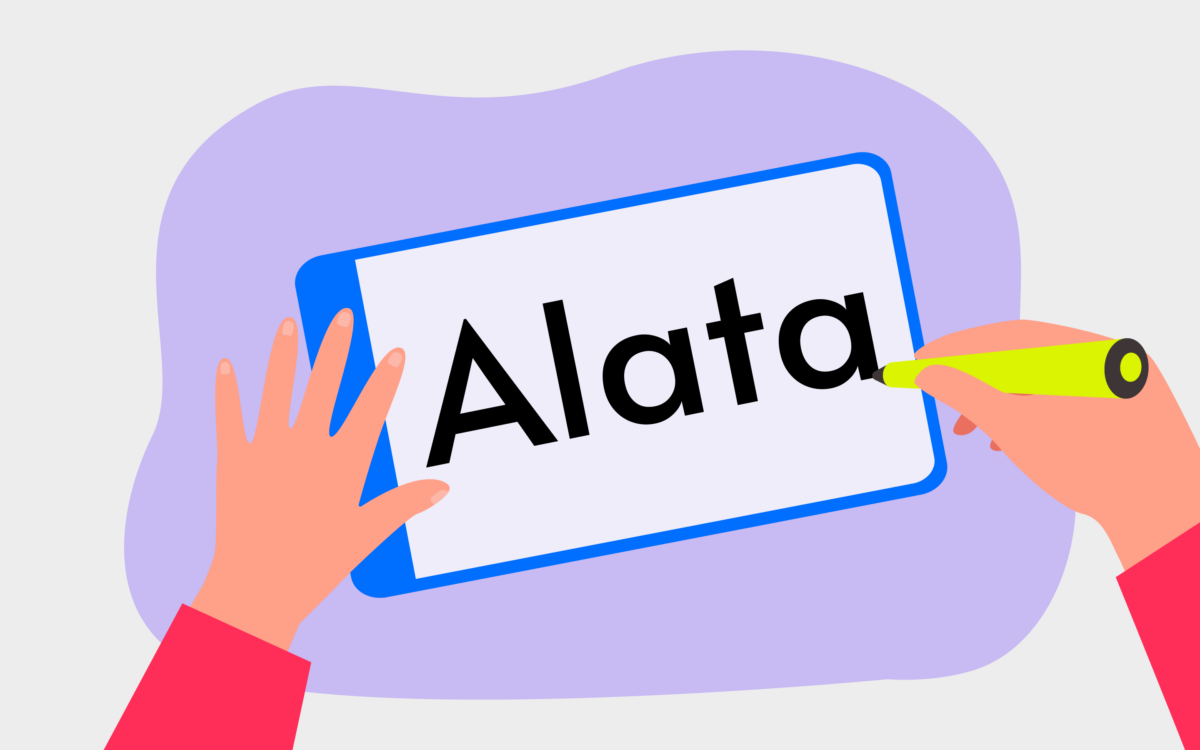
1. Alata
Alata es el primer lugar en el que comenzaremos en esta lista de las mejores fuentes en Canva. La fuente es bastante estándar y presenta un diseño elegante. Este es un excelente punto de partida si está buscando algo que no sea quisquilloso.
Si elige Alata, creemos que funcionaría mejor en la copia de la página de destino y para una infografía. La razón principal de esto es que es fácil de leer y se destaca desde lejos. También puede pensar en usarlo en anuncios.
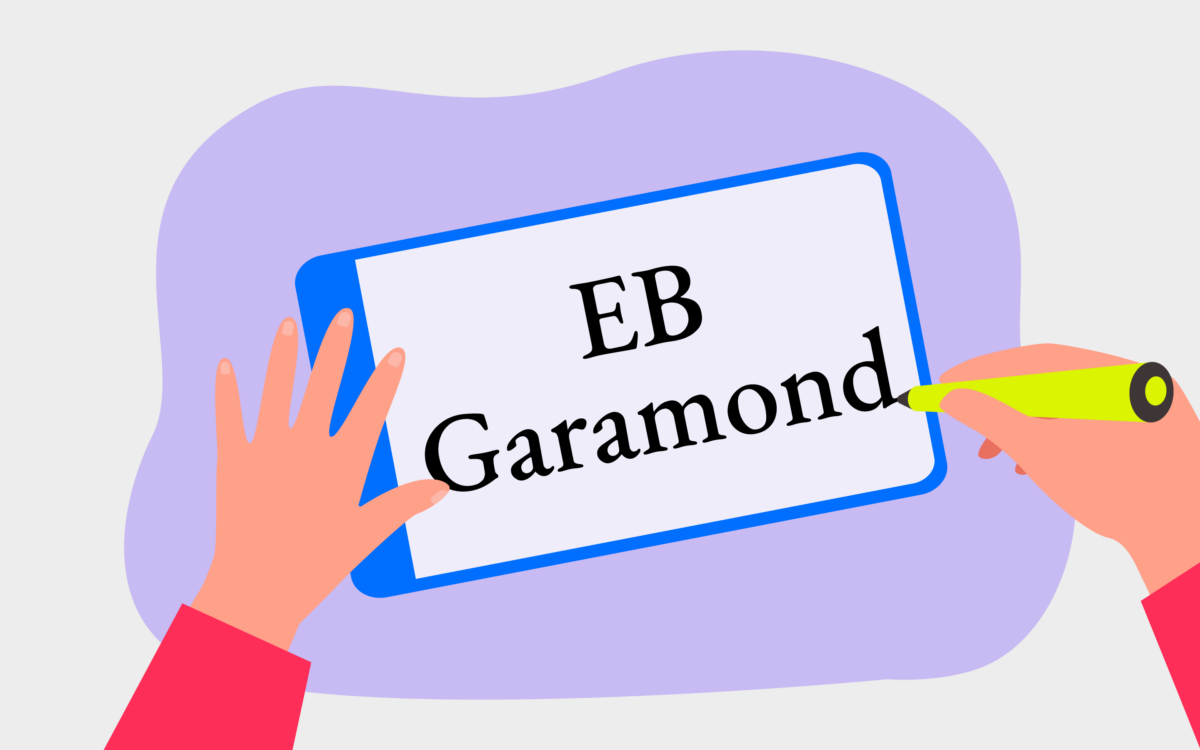
2. EB Garamond
Si ha usado Microsoft Word en el pasado, seguramente habrá oído hablar de Times New Roman. También estará bastante familiarizado con su apariencia. EB Garamond es una versión bastante similar y es una de las mejores fuentes de Canva para principiantes.
EB Garamond trabajará con marcas que busquen una apariencia más antigua. También puede usarlo en la copia de su página de destino y en cualquier currículum que diseñe dentro de Canva.
3. Serif PT
Si EB Garamond es demasiado anticuado para usted, considere usar PT Serif en su lugar. Este diseño es un poco más elegante y delgado que la fuente Canva mencionada anteriormente, lo que significa que es una mejor opción si su marca es más moderna.
PT Serif puede funcionar con encabezados de LinkedIn si es más una empresa de estilo corporativo. También puede usar esta herramienta con equipos relacionados con la escritura, como soluciones de edición. Y si es un escritor o editor independiente, es posible que desee usarlo de manera similar, principalmente si trabaja en libros.
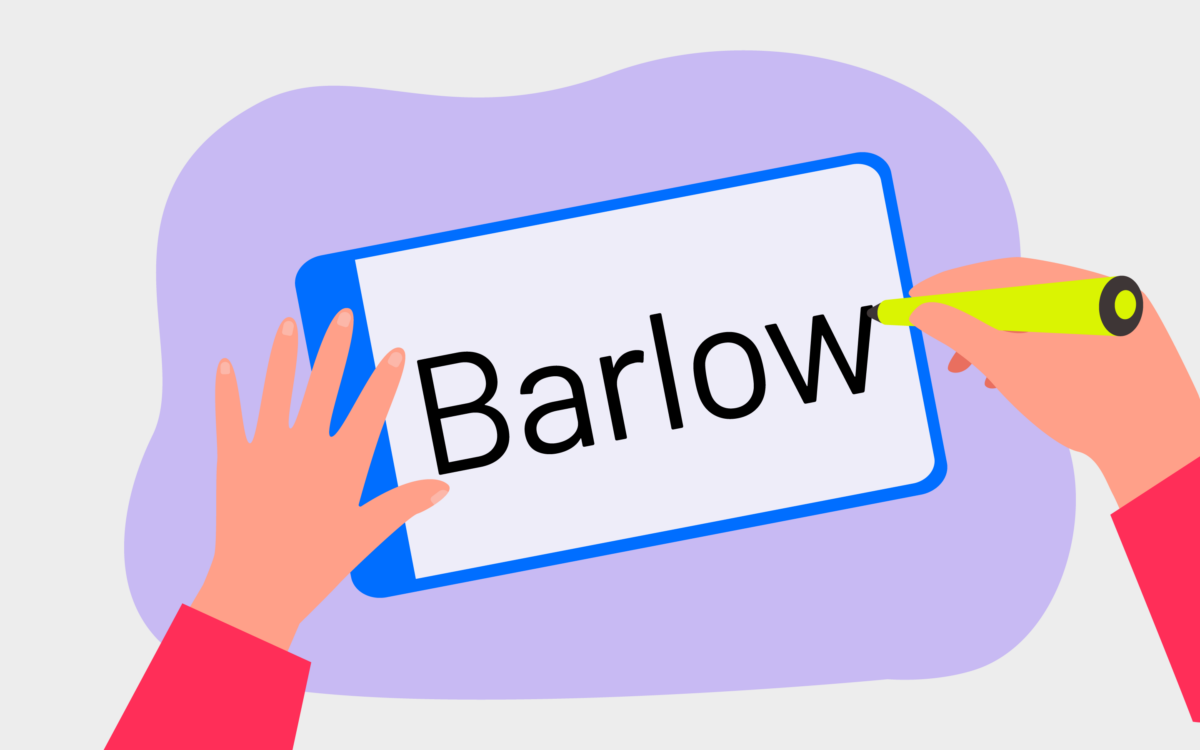
4. Negrita Barlow
Todavía no hemos cubierto ninguna fuente en negrita en nuestra lista de las mejores fuentes de Canva, por lo que pensamos que ahora sería un buen momento para cambiar eso. Barlow Bold es una de las fuentes en negrita más limpias de la aplicación y puede usarla para que su diseño se destaque como creativo.
Barlow Bold funciona con carteles y también es útil para títulos infográficos. También puede usarlo en los encabezados de los currículums. Además de eso, funciona con presentaciones. Es mejor usar esta fuente con moderación si es para el texto principal, ya que al lector le puede resultar complicado seguirla.
5. Arvo
Arvo es más aerodinámico que EB Garamond y PT Serif, pero no es muy diferente. Funciona mejor como parte del cuerpo principal del texto en lugar de usarlo en los encabezados.
La fuente es una excelente opción para campañas de infografía, y puede resultarle útil para usar en cualquier encabezado de redes sociales que pueda tener. También puede usar esta fuente si ejecuta un sitio web centrado en la tecnología.
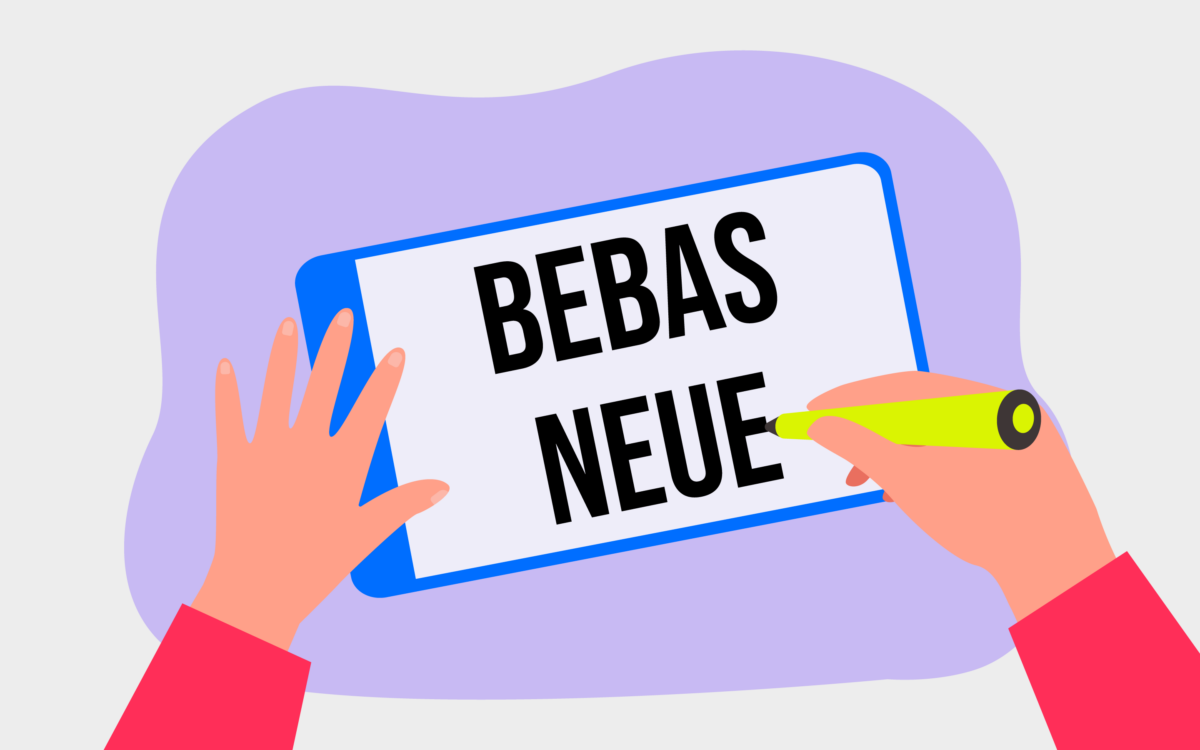
6. Bebas Neue
Otra fuente moderna en la que vale la pena pensar es Bebas Neue, y esta es bastante versátil. Funciona bien como encabezado o título, y puede resultarle especialmente útil si desea crear banners para sus canales de redes sociales, como YouTube.
También vale la pena usar Bebas Neue con cualquier infografía que quieras crear. Además de eso, puede usar la fuente con logotipos que desee diseñar, junto con muchos otros escenarios.
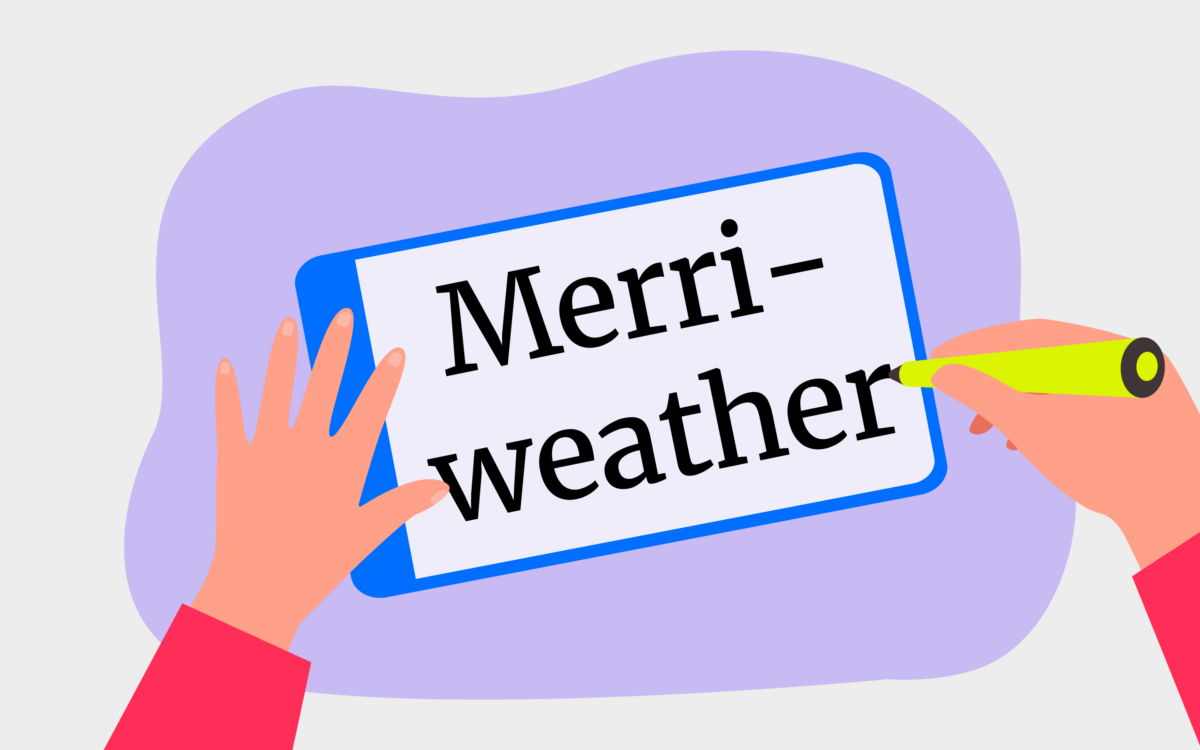
7. Buen tiempo
Merriweather es una fuente similar a algunas marcas de ropa para exteriores. Se destaca sin demasiados problemas, y la fuente también es una excelente opción si desea adoptar un enfoque práctico para sus proyectos de diseño.
Cuando use esta fuente, piense en usarla en campañas de marca y para sus logotipos. También puede funcionar al crear páginas para su sitio web y solicitar a los usuarios que realicen una llamada a la acción, como suscribirse a un boletín informativo.
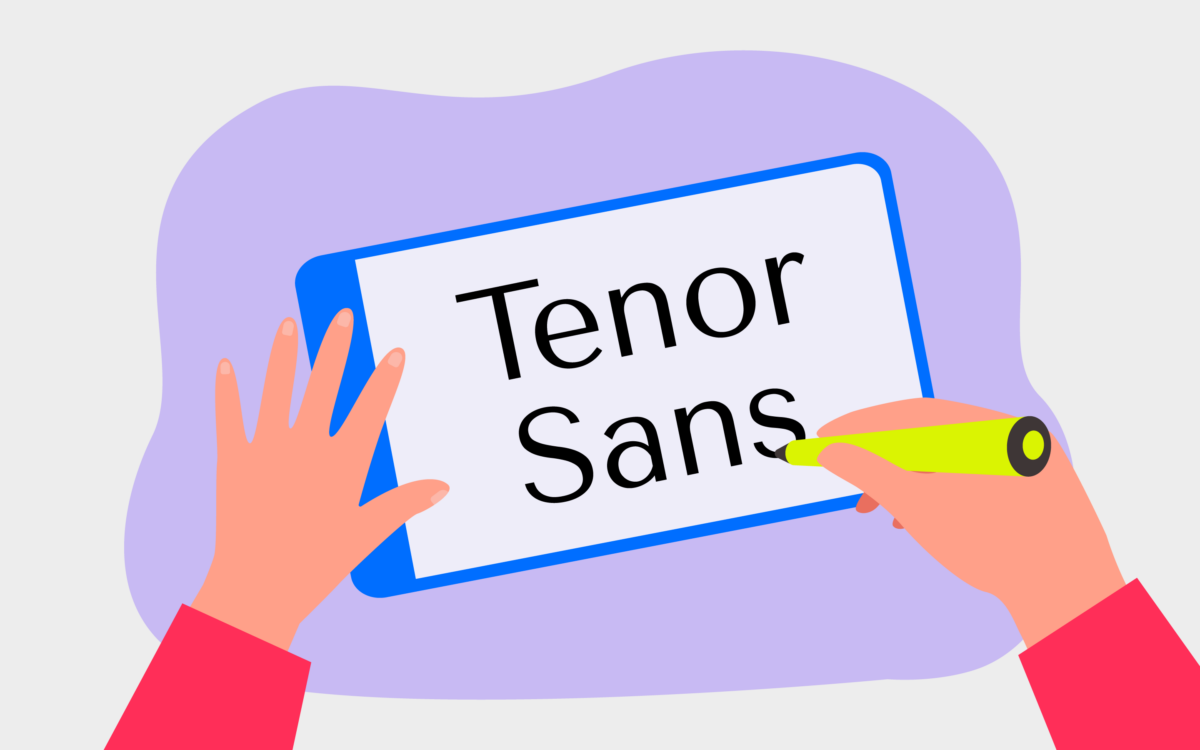
8. Tenor Sans
Tenor Sans es un excelente punto de partida potencial si desea algo que fluya un poco más libremente que Merriweather. La fuente es perfecta como título principal o como algo que usaría en su texto. Es algo moderno pero quizás un poco menos que otros en nuestra lista.
Puede usar Tenor Sans en los encabezados de las redes sociales, que también funciona bien con infografías. Más allá de esas posibilidades, también podría considerar agregar Tenor Sans a las publicaciones de las redes sociales y videos de formato corto, como Instagram Reels.
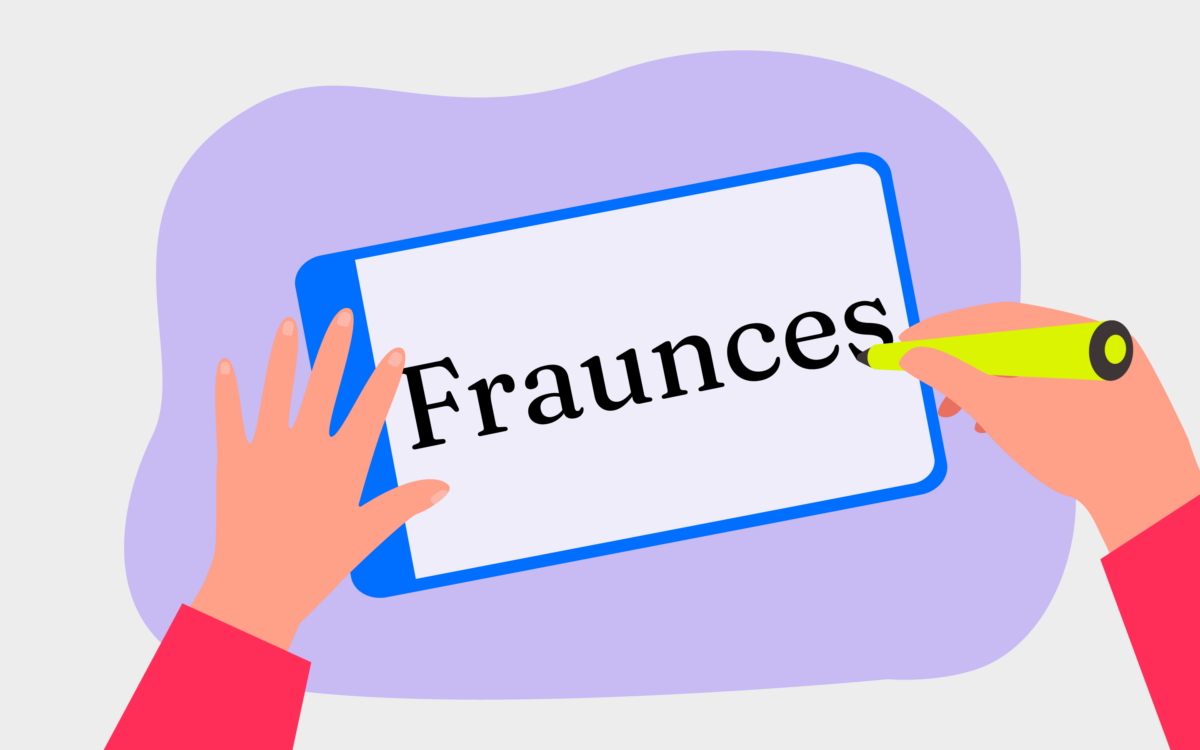
9. Fraudes finos
Otra de las mejores fuentes de Canva que se parece mucho a Times New Roman es Fraunces Thin. Como habrás adivinado por el nombre, la fuente es una respuesta más delgada a EB Garamond y las otras fuentes similares que hemos mencionado en esta lista hasta ahora.
Considere usar Fraunces Thin en sus videos cortos y cualquier diseño con mucho texto que necesite crear. También funciona para páginas de destino y varias otras formas de diseño en línea.
Si Canva suena como la herramienta adecuada para ti, ¿por qué no lo pruebas por ti mismo? ¡Es totalmente gratis durante 30 días!
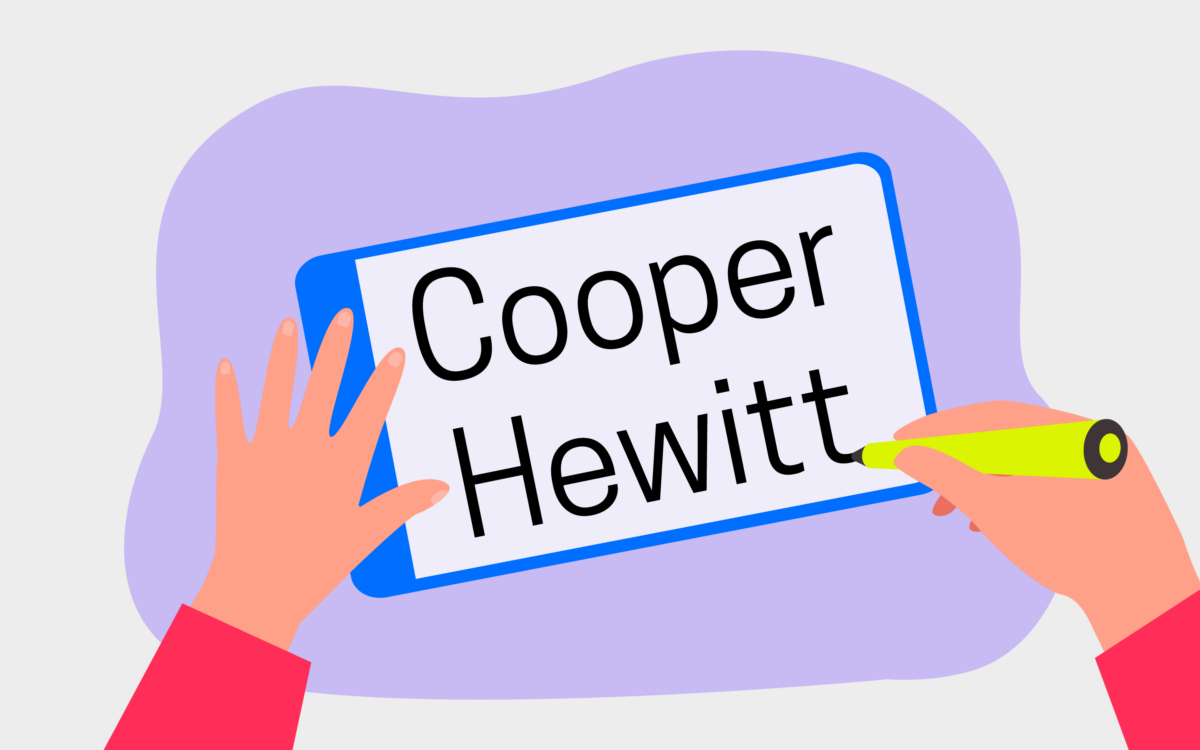
10. Cooper Hewitt
Cooper Hewitt es una de las mejores fuentes de Canva para quienes desean crear un diseño más moderno. La fuente funciona mejor como parte de un cuerpo principal de texto, por lo que debería considerar usarla en sus publicaciones e infografías en las redes sociales. También puede funcionar para cualquier boletín informativo que desee compartir con sus clientes.
También puede usar Cooper Hewitt en diseños para empaques, junto con varias otras cosas.
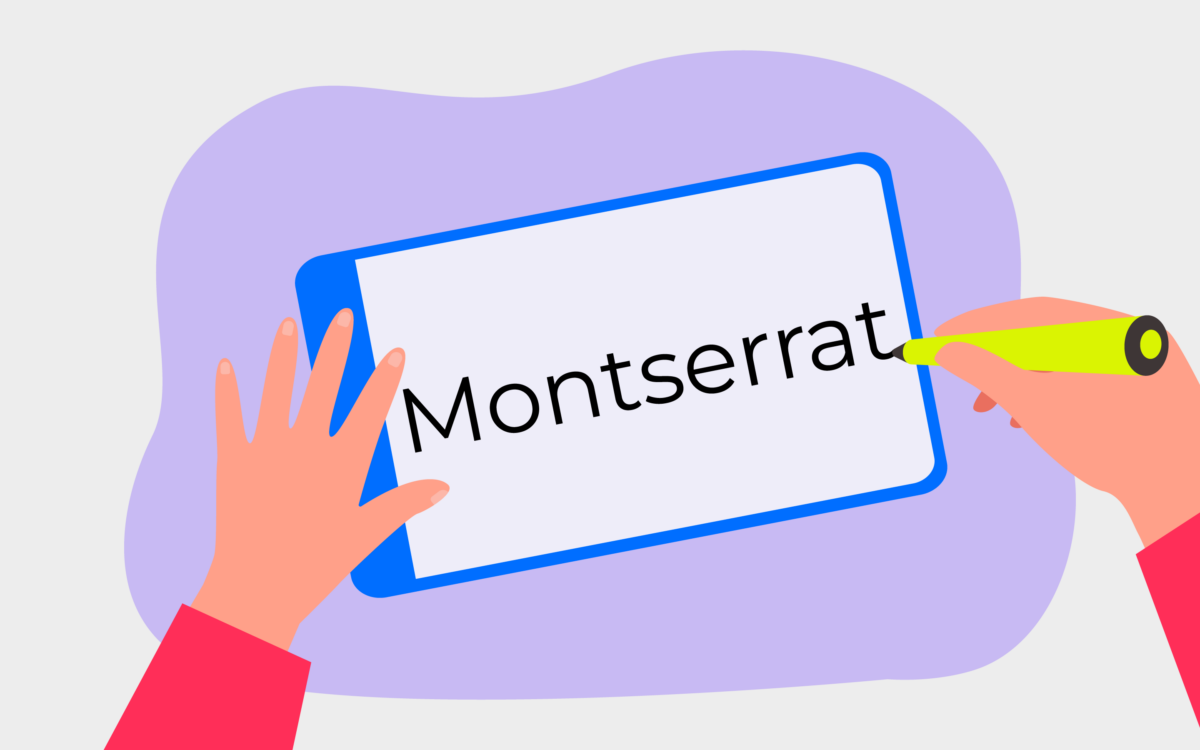
11. Montserrat
Montserrat es una alternativa un poco más elegante a Cooper Hewitt, y se puede usar en mis escenarios. Por ejemplo, puede pensar en usarlo todo en mayúsculas para los encabezados de sus redes sociales. También puede resultarle una opción práctica al crear una página de inicio para su sitio web, especialmente si es un creativo independiente.
La fuente Montserrat puede funcionar como texto principal y encabezados, y encontrarás una amplia selección de otros estilos de Montserrat que puedes combinar. Los ejemplos incluyen Montserrat Semi-Bold y Montserrat Thin.
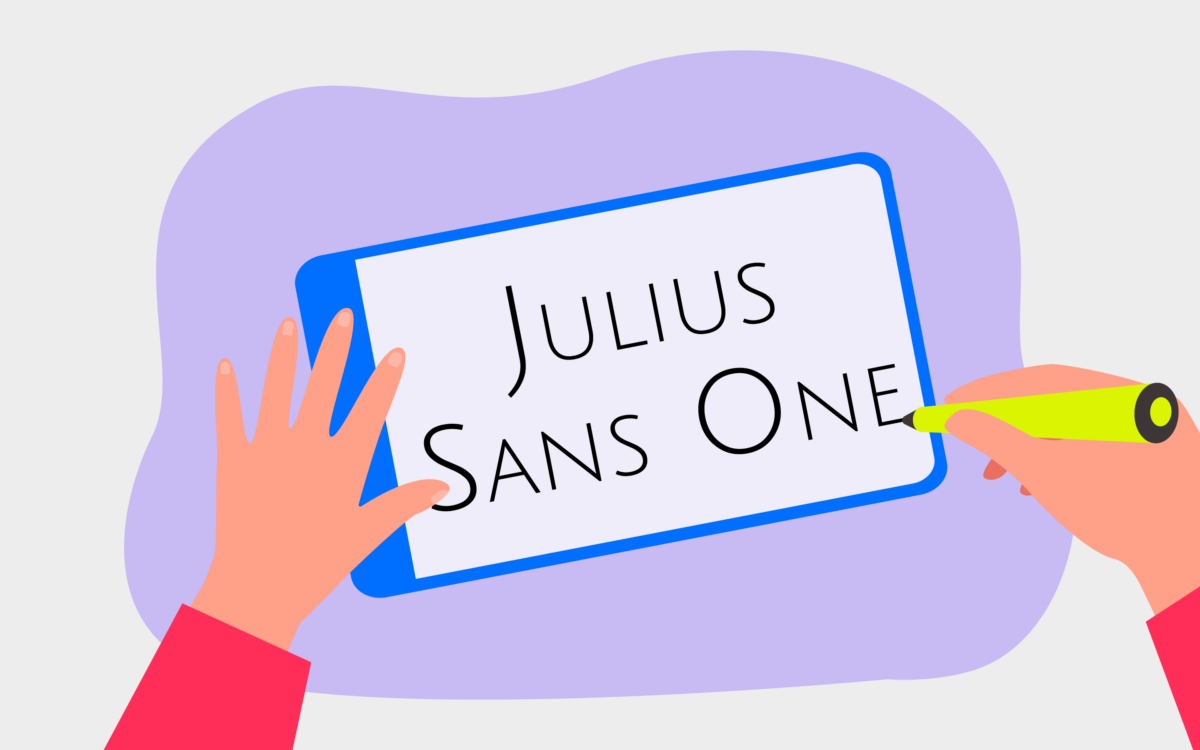
12. Julio Sans One
Vale la pena considerar Julius Sans One si está buscando algo que sea imponente y moderno en igual medida.
Puede notar que esto se parece a algo que esperaría usar en una película de suspenso para las escenas iniciales, y también funciona si está diseñando la portada de un libro en el mismo género.
Sin embargo, ese no es el único uso para Julius Sans One. También se puede usar en carteles y otros diseños que incluyen elementos visuales, como portadas de YouTube.
13. La serifa más joven
The Youngest Serif es una de las mejores fuentes de Canva si buscas algo que sea simple y directo. Si es un escritor independiente, es posible que desee considerar usar esto para su sitio web o como parte de su logotipo.
También puede usar esta fuente en sus infografías, y también es una buena opción para las miniaturas. Además, es posible que desee utilizar esta fuente para su canal de YouTube si habla de escritura o literatura.
14. Josefina Sans Regular
Josefin Sans Regular es otra de las fuentes más versátiles de Canva. Esta fuente es un poco más audaz que las otras que hemos mencionado en las últimas dos secciones. El espaciado también es un poco más amplio entre palabras y letras.
Puede usar Josefin Sans Regular en varios lugares, pero funciona especialmente bien como título o encabezado de su currículum. También se puede usar en las miniaturas de YouTube, y también puede resultarle útil para Instagram si está tratando de elegir algo que sea un poco menos cargado.
15. Fuente Serif Pro
Source Serif Pro es una de las fuentes más sofisticadas de Canva. Puede usar esto para exhibir una empresa de escritura, y también es una buena opción si desea que su marca llegue a una audiencia con mayor educación, como si su objetivo es atraer estudiantes a su universidad.
Esta fuente también funciona si estás solicitando un lugar en la universidad o un trabajo y quieres lucir confiable y respetable.
16. Fuente Sans Pro
Si Source Serif Pro está más cerca de Times New Roman, Source Sans Pro tiene muchas similitudes con Arial. La fuente es bastante simple y puede usarla con logotipos y en presentaciones.
Además de esas configuraciones, también puede encontrar que Source Sans Pro es una buena opción para las publicaciones que desee incluir en las redes sociales, y también es una opción útil para los trabajos de investigación.
17. Alfa Losa Uno
En comparación con muchas de las otras mejores fuentes de Canva ya mencionadas, Alfa Slab One se equivoca más en el lado atrevido. Tiene algo similar a Source Serif Pro and co. en términos de cómo se ve, pero también es mucho más audaz que esos.
Puede usar esta pestaña si ejecuta una publicación, especialmente si es algo fuera de línea, como un periódico. También funciona si está tratando de exhibir una marca en la mayoría de los otros subgéneros y nichos de medios.
18. Parisina
¿Alguna vez has visto una película francesa de principios del siglo XIX o XX o una película con un tema similar? Si es así, notará que muchos de ellos tienen una sensación un tanto romántica. Quizás también esté familiarizado con la fuente de escritura a mano sofisticada al final de programas como Looney Tunes.
La fuente Parisienne es la fuente perfecta para los creadores de cortometrajes y también funcionará para muchas otras personas en la industria del cine.
19. Cabina Normal
Cabin Regular es una de las mejores fuentes en Canva para hacer que tu trabajo y tus diseños se destaquen. Esta es una fuente relativamente simple y te ayudará a llamar la atención de tu audiencia en múltiples lugares.
Puede usarlo para infografías y libros electrónicos, y el diseño también funciona si está tratando de hacer un banner de canal de YouTube, aunque es posible que desee usar algo más para sus miniaturas.
Si Canva suena como la herramienta adecuada para ti, ¿por qué no lo pruebas por ti mismo? ¡Es totalmente gratis durante 30 días!
20. Migra Extralight
Una fuente que es bastante diferente de Cabin Regular es Migra Extralight. La fuente es una versión más delgada de las que hemos mencionado que se asemeja a Times New Roman. Debido a que se ve bastante elegante, una de las mejores cosas es que esto funciona tanto para los estilos de marca más nuevos como para los más antiguos.
Puede usarlo para diseños de sitios web, su currículum y varios otros escenarios.
21. Héroe
Hero es otro diseño que deberías considerar usar si buscas una apariencia moderna. Funciona para las empresas que intentan retratar un aspecto más moderno, como los gimnasios; además de usarlo en la marca de su logotipo, también puede funcionar en artículos como botellas de agua y camisetas.
Esta marca también es una buena opción para las empresas de tecnología, especialmente aquellas en el espacio de software como servicio (SaaS).
22. Garet
Si está buscando algo similar a la fuente Hero que acabamos de mencionar, Garet es probablemente la mejor alternativa en Canva. Es un poco más grueso que Hero, pero aún se puede usar en múltiples escenarios. Por ejemplo, puede usarlo para crear anuncios publicitarios en línea que aparecen en otros sitios web.
También es útil si necesita crear un logotipo rápido pero no está seguro de qué desea usar.
23. Liga espartana
League Spartan es una fuente más audaz que Hero y Garet, pero aparte de eso, no es muy diferente. Esta fuente es mejor para los logotipos y notará que se ve bastante similar a la que se usa para monday.com, una solución de software de gestión de proyectos.
24. Bodoni FLF
Bodoni FLF es una de las mejores fuentes en Canva si buscas algo más boutique. Podría considerar usar esto en su logotipo, especialmente si es una marca de lujo. Funciona para corporaciones de alto nivel, como bufetes de abogados y asesores financieros.
También puede considerar usarlo si es un contratista en los campos legal y financiero.
Desbloquee el acceso ilimitado a una amplia biblioteca de fuentes y elementos de diseño de Canva por solo $ 16.50 por mes con una suscripción a Envato Elements . Obtenga más de 50 millones de artículos, incluidos efectos de stock y paquetes de elementos, y descárguelos con la frecuencia que necesite. ¡No se lo pierda, suscríbase ahora y comience a diseñar con facilidad!
25. Archivo Negro
Archivo Black es otra fuente en negrita en nuestra lista, y está un poco más espaciada de lo que encontrarás si usas League Spartan. Al igual que League Spartan, es posible que encuentre esta fuente especialmente valiosa si está tratando de crear un logotipo.
Más allá de eso, sin embargo, también es una buena opción para títulos y encabezados, incluso en cualquier portada de publicación de blog o miniaturas de YouTube que desee crear.
26. Alerón delgado
Si desea algo similar a Archivo Black pero más simplificado, Aileron Thin es una de las mejores fuentes de Canva para elegir. Es mucho más delgado y puede resultarle útil en varios escenarios.
Es conveniente si está en el campo creativo y es posible que desee usarlo para su sitio web y encabezados de YouTube.
27. Roboto
Aileron Thin es una de las opciones más delgadas de nuestra lista, por lo que puede haber mejores opciones para su diseño. Si desea algo estrecho pero menos delgado que la fuente mencionada anteriormente, Roboto es una opción práctica.
Es una fuente valiosa para cualquier cosa relacionada con la tecnología, y es posible que también desee usarla si busca un trabajo en cualquier industria relacionada.
28. Carmesí profesional
Crimson Pro es otra de las mejores fuentes en Canva si quieres una alternativa a Times New Roman. La fuente es estándar y funciona bien para campos como legal. Puede usarlo tanto para los encabezados como para el texto principal, y puede resultarle especialmente útil si necesita crear un currículum.
También es una excelente opción para diseños con mucho texto.
29. Abierto Sans
Open Sans es una de las mejores fuentes más básicas de Canva. Sin embargo, eso no significa que valga la pena saltárselo. La fuente es versátil, y algunas ocasiones en las que puede querer usarla incluyen al hacer infografías y diseños de empaques.
Más allá de eso, considere usar Open Sans para banners y escenarios similares.
Si Canva suena como la herramienta adecuada para ti, ¿por qué no lo pruebas por ti mismo? ¡Es totalmente gratis durante 30 días!
30. Cincela
A medida que nos acercamos a redondear nuestra lista de fuentes de Canva, hablemos un poco de Cinzel. Cinzel tiene una sensación más majestuosa y le resultará una gran herramienta si diseña portadas de libros. También es posible que desee usarlo si está creando una película sobre magia o algo similar.
Y si ejecuta un servicio relacionado con cualquier cosa relacionada con la fantasía, considere mirar esto.
31. Surana
Algo similar a Crimson Pro es Suranna, que al mismo tiempo es un poco más audaz. Si desea utilizar esta fuente, la encontrará útil en muchas situaciones en las que desee utilizar Crimson Pro.
32. Poiret Uno
Poiret One no es como ninguna de las mejores fuentes de Canva que hemos discutido. Es uno de los más modernos y tiene un aire minimalista al estilo escandinavo. Si es una empresa de muebles con ese tipo de tema, es posible que desee que esta sea su fuente preferida para su logotipo.
También funcionará bien si estás en un espacio relacionado con la tecnología.
33. Cuatrocento
Quattrocento es como un cruce entre Crimson Pro y Poiret One. Es elegante y funciona bien como logotipo de marca, pero también puede resultarle útil si desea utilizarlo para algo relacionado con la tecnología, pero desea ser un poco más vanguardista que Poiret One. También es una gran fuente para cualquier empresa que intente lucir más moderna.
34. Grotesco más oscuro
El nombre no suena atractivo, pero Darker Grotesque es una de las mejores fuentes en Canva. Es relativamente tenue y funciona bien si quieres algo moderno pero que no se destaque demasiado. El espaciado está un poco más cerca que algunas de las otras fuentes de nuestra lista.
35. Osvaldo
Oswald es una fuente fantástica para resaltar tus estadísticas. Por esa razón, funciona bien con infografías y es una buena opción para documentos técnicos y otros documentos de investigación. También puede usar Oswald para carteles, presentaciones, etc.
36. Exhibición de juegos limpios
Playfair Display es similar a Quattrocento, pero parece un poco más antiguo. Puede usar esta fuente para cosas como carteles musicales y títulos de logotipos, y también vale la pena considerarla si desea mejorar el título de su currículum.
37. Liga gótica
League Gothic presenta espacios reducidos y un estilo de fuente similar a Arial. Puede usarlo para las miniaturas de YouTube, que también funcionarán para sus encabezados. Más allá de eso, considera usar League Gothic para tus banners de redes sociales y las imágenes que compartes en la plataforma.
38. Libre Baskerville
Libre Baskerville es otra fuente de Canva con similitudes con Times New Roman. Vale la pena echarle un vistazo si eres un agente de bienes raíces, y lo mismo ocurre si quieres crear un sitio web como agente de bienes raíces. Más allá de eso, también es una buena opción para logotipos de empresas en otros campos, como las finanzas.
39. Lora
Lora es un poco más apagada que Libre Baskerville. Puede usarlo como texto principal en sus páginas de destino, y también vale la pena considerarlo si está preparando un libro. Más allá de eso, considera usar Lora para tus cartas de presentación y en los contratos que quieras armar en Canva.
Si Canva suena como la herramienta adecuada para ti, ¿por qué no lo pruebas por ti mismo? ¡Es totalmente gratis durante 30 días!
Prueba las mejores fuentes de Canva y haz que tus creaciones destaquen mejor
Es imposible responder a las cinco mejores fuentes de Canva, ya que lo que te gusta diferirá de otra persona. Sin embargo, encontrará muchas fuentes para múltiples escenarios, y no debería resultarle demasiado difícil obtener su diseño correcto.
Esta lista te dará una ventaja considerable a la hora de encontrar las mejores fuentes en la aplicación.
Al usar las fuentes populares de Canva en esta lista, puede dar vida a sus ideas creativas, independientemente de lo que esté tratando de lograr. Puede crear logotipos, infografías y mucho más.